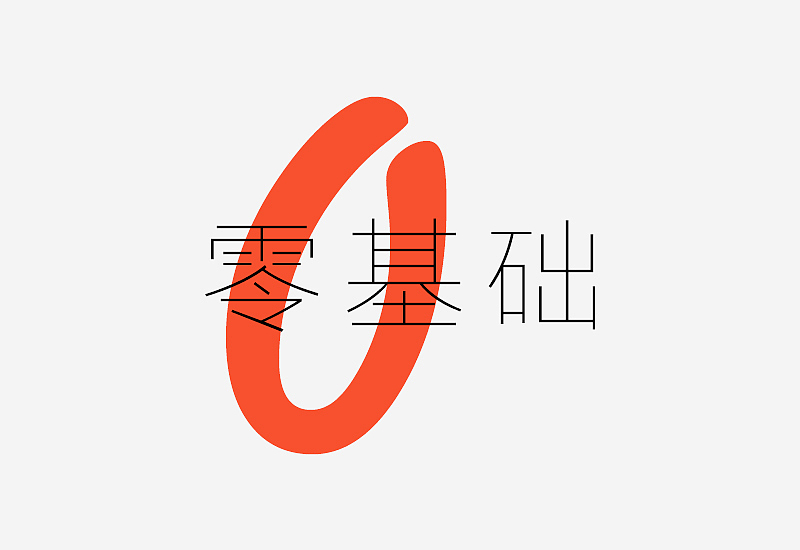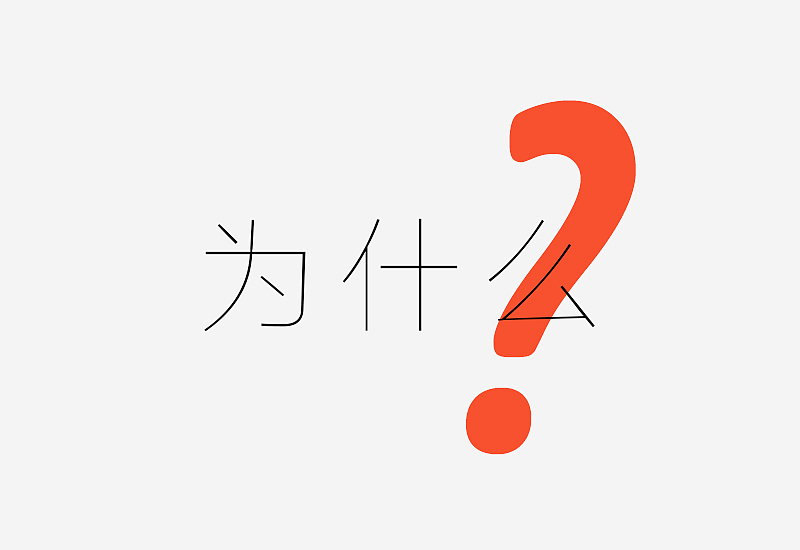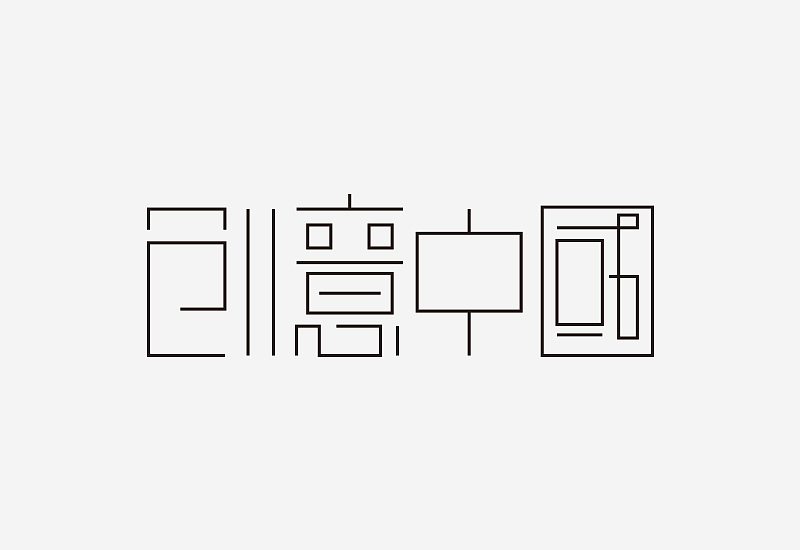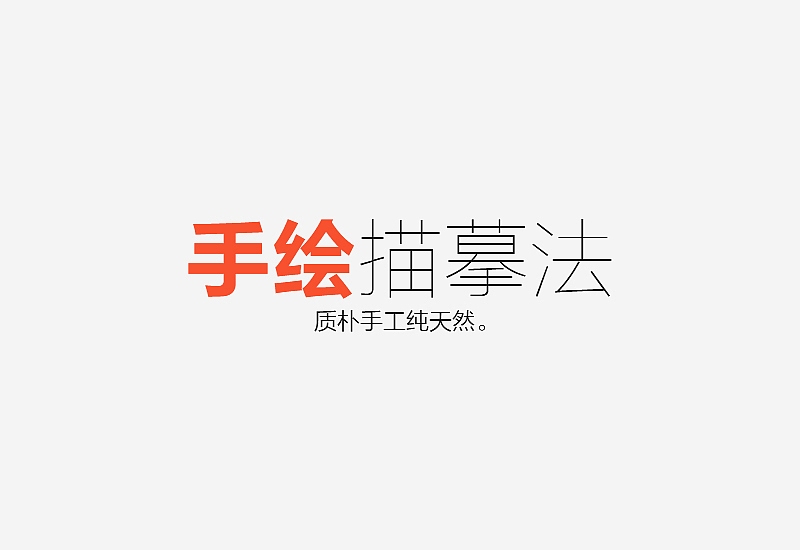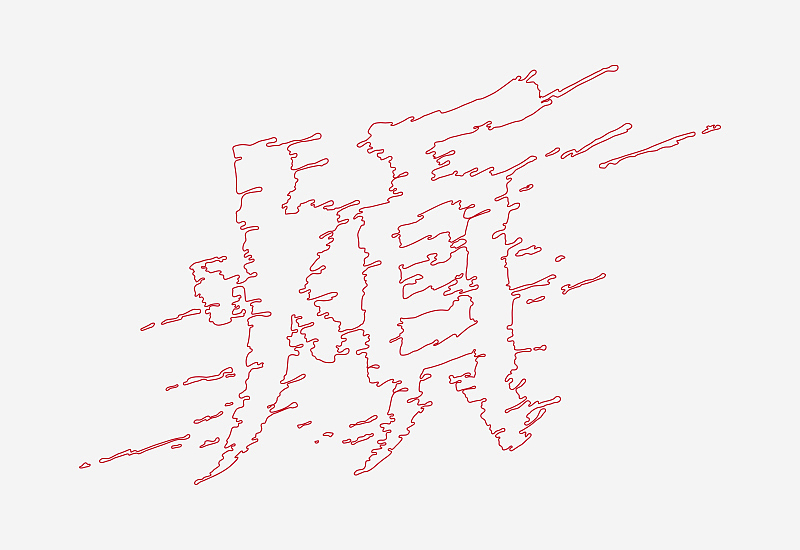
小白的“字”学之路
常规基础的方法稍加变通就可以创造出风格各异的字体,掌握了这几种比较基础的造字法相信在字体设计方面可以更从容的应对。
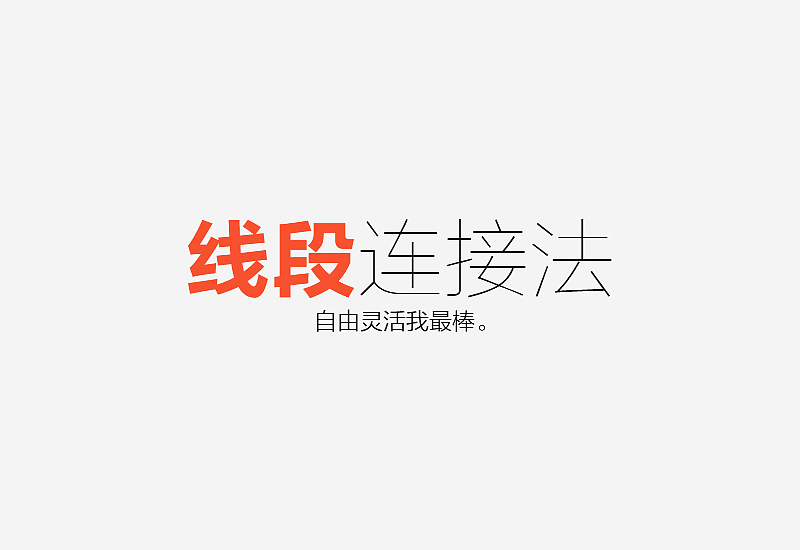备好板凳、我们走起~
备好板凳、我们走起~
只要喜欢字体设计,有一定的热情,相信字体设计对你来说不是什么困难的事情。
为什么要学习字体设计?相信对于每个人来说都会有不一样的答案,不知道你是否还记得最初接触字体设计的原由,我大概总结了几种,看看下面的理由是不是够充分呢?
它存在于我们生活的方方面面、角角落落,除了早上醒来第一眼看见的是天花板,其他时间我们想看不见他都难。
现如今人们更多地是追求一对一的个性化服务。
做一套字库本身就是一件费时费力的事情,当然不是说我们想怎么用就怎么用的,如果抱有侥幸心理任性用了,哪一天被逮到,不是道歉和眼泪就能解决的问题,这样的例子不在少数。
这个理由真的很虐心,像以前客户,感觉有个图形、有个名就可以了,要求上就没那么多;而如今的客户不仅有钱而且有文化,确实在很多领域要比我们懂得多,品牌意识强。
多一点热爱,相信字体设计会给你带来更多了乐趣。
不必纠结于使用什么软件,只是一个设计工具,因人而异适合最好。
下面给大家解密5种比较常规但又很实用的方法,以作参考。另外每种方法都会展示三个大概步骤,让大家看起来更直观些。
块面组合法是字体设计中最为基础也是最常规的设计方法。块面组合法基本说来就是以几何块面为基本的笔画搭字,然后再进行深入的调整和变化,呈现出不同形式感觉的字体。
具体来讲,块面组合法就是先使用矩形工具设定好笔画的粗细,然后进行组合造字,构建好基本的结构字形,接着做进一步的调整和细化,尝试对一些笔画进行断笔、共用和删减等处理,不断丰富字体的细节特征。此种方法操作简单,且易于控制,特别适用于初学字体设计的朋友,可以作为字体设计的入门方法进行不断地尝试与练习。
块面组合法是字体设计中最为基础也是最常规的设计方法。块面组合法基本说来就是以几何块面为基本的笔画搭字,然后再进行深入的调整和变化,呈现出不同形式感觉的字体。
具体来讲,块面组合法就是先使用矩形工具设定好笔画的粗细,然后进行组合造字,构建好基本的结构字形,接着做进一步的调整和细化,尝试对一些笔画进行断笔、共用和删减等处理,不断丰富字体的细节特征。此种方法操作简单,且易于控制,特别适用于初学字体设计的朋友,可以作为字体设计的入门方法进行不断地尝试与练习。
01. 使用“矩形工具”建立出基本的笔画。
02. 根据建立的笔画进行组合造字。
03. 细节调整,填色,完成设计。
如果把“块面组合法”想象成小游戏“俄罗斯方块”,那么“线段连接法”就如同“贪吃蛇”一般灵活多变。这种方法主要应用软件中的”钢笔”工具,通过改变线段粗细、曲直和断连关系,从而设计出不同风格的字体。
<br>灵活多变是线段连接法最大的特色,除了基本的直线,可根据实际需求来变化曲线和折线等。所以不管是横平竖直的常规方块字体,还是曲线夸张的风格字体,都可快直接快速地勾勒出来,这一步选用钢笔工具完成即可;当确定好了基本字形,再调整描边的粗细和端点的曲直,反复进行调试和对比,使字体达到最佳的状态。<br><br>需要特别注意的是,当整个字笔画都是以均匀的线段为主时,线段之间的穿插分布切忌过密过疏,尽量保持匀称,适当增加字体内部空间,透气性佳整体才会更显轻盈雅致。
如果把“块面组合法”想象成小游戏“俄罗斯方块”,那么“线段连接法”就如同“贪吃蛇”一般灵活多变。这种方法主要应用软件中的”钢笔”工具,通过改变线段粗细、曲直和断连关系,从而设计出不同风格的字体。
灵活多变是线段连接法最大的特色,除了基本的直线,可根据实际需求来变化曲线和折线等。所以不管是横平竖直的常规方块字体,还是曲线夸张的风格字体,都可快直接快速地勾勒出来,这一步选用钢笔工具完成即可;当确定好了基本字形,再调整描边的粗细和端点的曲直,反复进行调试和对比,使字体达到最佳的状态。
需要特别注意的是,当整个字笔画都是以均匀的线段为主时,线段之间的穿插分布切忌过密过疏,尽量保持匀称,适当增加字体内部空间,透气性佳整体才会更显轻盈雅致。
01. 使用“钢笔”工具建立字体“骨骼”,细线条勾勒便可,注意笔画间的穿插变形。
02. 确定好了基本骨骼,接下来适当的将笔画加粗并调整细节规范。
03. 选取颜色填色,并且加上一个中式外框和英文字,形式感更强。
对于一些需要表现手工质朴感的字体,手绘描摹法再合适不过了。通过其名称不难理解,手绘描摹法大概就是先在纸上手绘出完整的字体样式,然后录入电脑,将手绘稿在软件中进行描摹绘制,并适当加以修饰。
<br>手绘相较于电脑绘制总有不一样的感觉和优势,特别是对于一些复杂的字体设计,手绘更加灵活效率也更高一些,先用手绘再通过电脑将字体进行还原,这样手工质朴的感觉可以得到最大化保留。<br><br>这种方法重点在于纸上的手绘,字体形式和细节上的变化和处理基本都在纸上完成,软件描摹则尽量地还原手绘稿的原貌,当然最后对于细节上的问题也要及时地加以修正。
对于一些需要表现手工质朴感的字体,手绘描摹法再合适不过了。通过其名称不难理解,手绘描摹法大概就是先在纸上手绘出完整的字体样式,然后录入电脑,将手绘稿在软件中进行描摹绘制,并适当加以修饰。
手绘相较于电脑绘制总有不一样的感觉和优势,特别是对于一些复杂的字体设计,手绘更加灵活效率也更高一些,先用手绘再通过电脑将字体进行还原,这样手工质朴的感觉可以得到最大化保留。
这种方法重点在于纸上的手绘,字体形式和细节上的变化和处理基本都在纸上完成,软件描摹则尽量地还原手绘稿的原貌,当然最后对于细节上的问题也要及时地加以修正。
01. 第一步就是先在纸上绘制出整个字体,对于一些复杂的字体特别需要静下心耐心绘制。
02. 将手绘好的字体放入软件中进行描摹,并修饰轮廓和细节。
03. 最后填色完成设计,当然你也可以再使用Photoshop软件进行处理,使字体效果上更加出色,视觉冲击力更足。
字库内的字体结构严谨规矩,因其主要以方便阅读为目的,所以缺少一些个性的释放。而字库改造法就是以中文字库内的字体为设计基础,加以改造和修饰,这样不管是在形式上还是风格上都有别于原有字体,个性鲜明突出,焕发新活力。
<br>老实说这是一种比较“偷懒”的设计方法,却也是一种比较有效和快速的设计方法,特别是在一些电商行业的字体设计中会常用到此方法。归纳下来字库改造法其实就是对原字体进行加法与减法的整合,加法就是指改变原有字库字体的笔画特征,并增加笔画细节,而减法则是指将原笔画进行合理的断笔,巧妙的共用,灵活的删减,最终达到简化的目的,以一加一减的形式完成对字库字体的改造。
字库内的字体结构严谨规矩,因其主要以方便阅读为目的,所以缺少一些个性的释放。而字库改造法就是以中文字库内的字体为设计基础,加以改造和修饰,这样不管是在形式上还是风格上都有别于原有字体,个性鲜明突出,焕发新活力。
老实说这是一种比较“偷懒”的设计方法,却也是一种比较有效和快速的设计方法,特别是在一些电商行业的字体设计中会常用到此方法。归纳下来字库改造法其实就是对原字体进行加法与减法的整合,加法就是指改变原有字库字体的笔画特征,并增加笔画细节,而减法则是指将原笔画进行合理的断笔,巧妙的共用,灵活的删减,最终达到简化的目的,以一加一减的形式完成对字库字体的改造。
01. 我们选用了细明体“算命先生”四字为改造的基础字形,大家可以根据自己的需求来选择需要改造的字体,字体虽不同但方法基本一致。
02. 接下来将字体扩展然后做拆减处理,对字体进行重构。
03. 细节处理与调整,这一示例主要是将直角转变为变圆角,借用查件Xtream Path即可快速实现,其他无需做太大的修整。
在西文字库中有很多形式感非常强的字体,我们可以借用其中的字母充当中文的基本笔画,加以融合改造,制造出别有韵味的中文字体。
<br>在使用此方法进行字体改造和设计时,首先把西文里的大小写字母全部展开以备用,然后选取其中的完整字母或是截取字母当中的某一部分进行中文字体的搭建。有时候会遇到其中的某些西文笔画并不完全符合传统中文的笔画走势,像这种情况下可在不影响识别性的原则下,打破常规,多保留原有西文字体的特征,当然也并不是所有的笔画都是完全的合适,具体到一些笔画可根据西文制造出相应的中文笔画。<br><br>总结下来就是以中文结构笔画为基本需求,灵活借用西文字体并对中文字体做以改变和调整,并保留西文特色,以达到西文中用的目的。
在西文字库中有很多形式感非常强的字体,我们可以借用其中的字母充当中文的基本笔画,加以融合改造,制造出别有韵味的中文字体。
在使用此方法进行字体改造和设计时,首先把西文里的大小写字母全部展开以备用,然后选取其中的完整字母或是截取字母当中的某一部分进行中文字体的搭建。有时候会遇到其中的某些西文笔画并不完全符合传统中文的笔画走势,像这种情况下可在不影响识别性的原则下,打破常规,多保留原有西文字体的特征,当然也并不是所有的笔画都是完全的合适,具体到一些笔画可根据西文制造出相应的中文笔画。
总结下来就是以中文结构笔画为基本需求,灵活借用西文字体并对中文字体做以改变和调整,并保留西文特色,以达到西文中用的目的。
01. 图为Chiller字体,比较随性、自然的手写字体。
02. 做中文字体搭建。图中红色笔画部分为西文原字母,蓝色笔画部分是经修改或局部截取的西文字母。
03. 加英文作为点缀,最后完成效果。